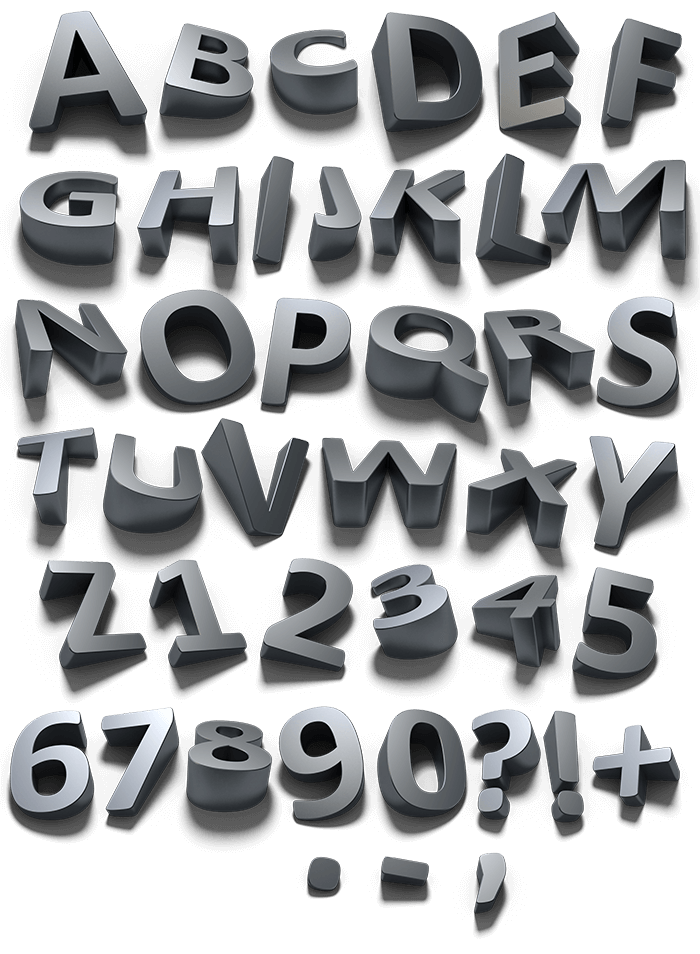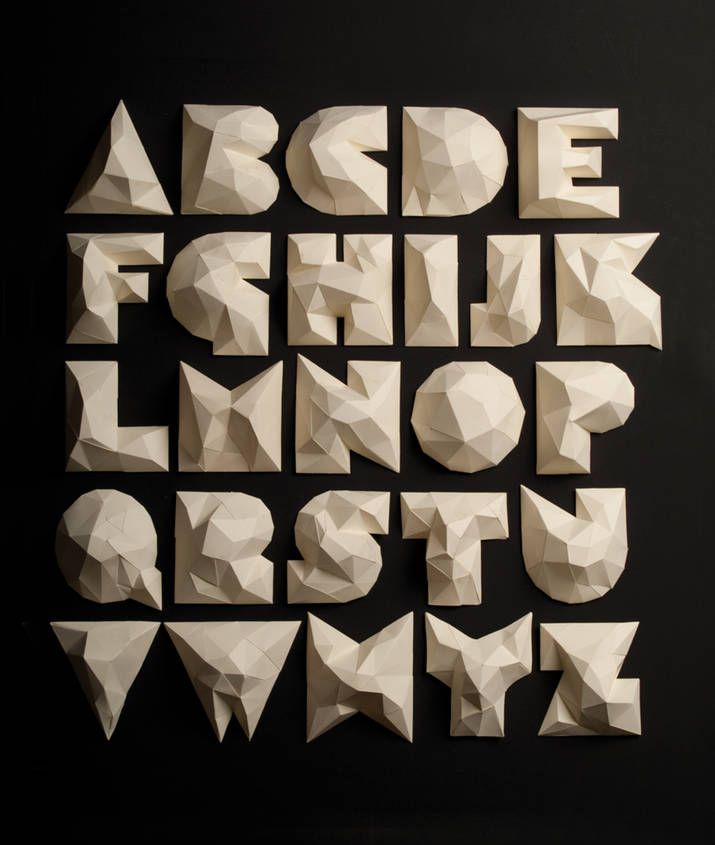
10 лучших шрифтов за эту неделю
Подготовили для вас интересные шрифты, которые подойдут для абсолютно разных целей.
Вы найдете как вариации классических гарнитур, так и выдающиеся декоративные примеры.
Шрифт, позволяющий комфортно читать объемные материалы. Свободные, легко читаемые буквы делают его подходящим для использования в статьях и лонгридах с большим количеством текстового контента. Для личного и коммерческого использования.
Шрифт с округлыми формами, передающий легкое и приключенче
Литеры шрифта построены исключительно на прямых линиях, однако ему не присуща суровость.
Наоборот, это милый и игривый шрифт, который добавит личному или коммерческому проекту неформальности.
Классический строгий шрифт с засечками, вдохновленный классицизмом и средневековой историей. Бесплатен для личных и коммерческих работ.
Оригинальный декоративный шрифт с плавными формами, как будто состоящий, как следует из названия, из веток. Можно использовать в личных и коммерческих целях, однако при создании логотипов есть нюанс.
Выразительный шрифт в стиле модерна, напоминающий об эпохе немого кинематографа. Можно использовать в личных и коммерческих проектах.
Декоративный шрифт с широкими и приземленными формами. Подойдет для неформальных стилизованных проектов. Для личного и коммерческого использования.
Шрифт с засечками, предназначенный для больших текстов. Достаточно простой и приятный.
Элегантный шрифт с тонким начертанием, который отлично подойдет для заголовков. Для личной и коммерческой деятельности.
Яркий шрифт, вдохновленный уличными вывесками и потому прекрасно подходящий для этикеток, плакатов и прочих лицевых материалов. Состоит из ломаных линий, расположившихся словно в импровизации. Можно использовать для личных потребностей и коммерческого направления.
Типограф, автор образовательных проектов по типографике Мэттью Баттерик определяет типографику, как визуальную составляющую напечатанного текста.
Хорошая, емкая формулировка с большим пространством для маневра. Именно из-за этого под термином часто понимают достаточно разные вещи.
То, что относится к UX, большей частью касается макротипографики — расположения текста на странице. Микротипографика — это тонкая настройка, работа на уровне символов.
Важна ли типографика пользователям и бизнесу? Конечно. Есть исследования, которые объясняют, как параметры шрифта приносят существенные конверсии, как управлять эмоциями пользователя и дают понять, что несоблюдение достаточного контраста в вебе будет дорого стоить. Подобные вещи действительно влияют на восприятие. Ключевой момент, с которым нужно разобраться, — как люди читают.
Как люди читают
Классические книги, статьи, в основном не останавливаются на физиологии. Чаще речь о диаграмме Гутенберга и различных паттернах чтения.
Диаграмма Гутенберга рассказывает о том, что при большом объеме контакт с текстом начинается с левого верхнего угла и ослабевает по определенным законам.
На основе этих данных строятся известные паттерны чтения: z-паттерн, f-паттерн… Это здорово, этим можно пользоваться, но ответа на вопрос, почему так происходит, — здесь нет.
Немецкий типограф Ян Чихольд еще в 1928 году пришел к выводу, что современный человек не хочет читать объемные тексты. «Сканирует» полотно, находит что-то полезное и только тогда останавливается и начинает читать. Вряд ли Чихольд интересовался исследованиями по физиологии, но, тем не менее, понимал, как все происходит.